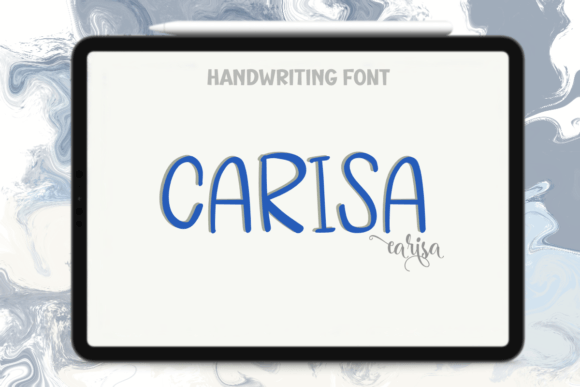
Carisa
Si buscas recursos de alta calidad como Carisa, este paquete premium es una opción fantástica para tus proyectos creativos.
Elaborado con precisión, Carisa proporciona vectores limpios, tipografía suave y una licencia comercial para tu tranquilidad.
Ya sea que estés creando productos POD (impresión bajo demanda), invitaciones de boda o gráficos para redes sociales, Carisa es una opción ideal.